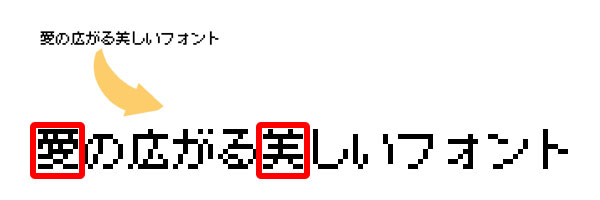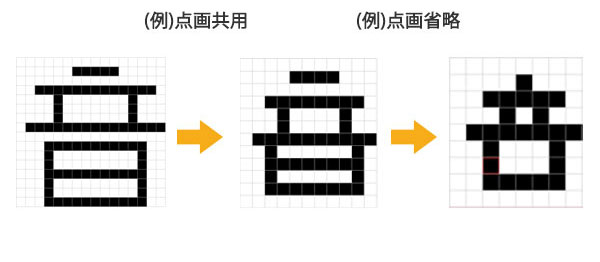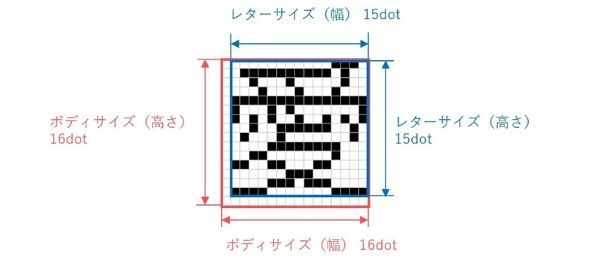
画像データですので、文字コードを受け取りましたら文字画像をそのまま表示します。
正しくない文字となってしまいますが、直感的に読めるように工夫されています。
線などを間引くことでつぶれないようにしてあります。
ビットマップフォント(1文字ずつの画像)を文字列にします。
文字間や行間の間隔調整などの処理もできます。
アラビア語やタイ語など複雑な表記ルールを持つ言語を正しく表示するために必要なソフトウェアです。
大小様々な表示機器で文字表示をされたいなどの目的で多くの文字サイズを扱う場合は、ビットマップフォントよりもスケーラブルフォントの方がデータ容量を抑えられます。
例 16,18,20,24,32,48,64dotで表示されたい場合
例 ゼロとオーを明確に区別したい
古い規格の字形で文字表示したい